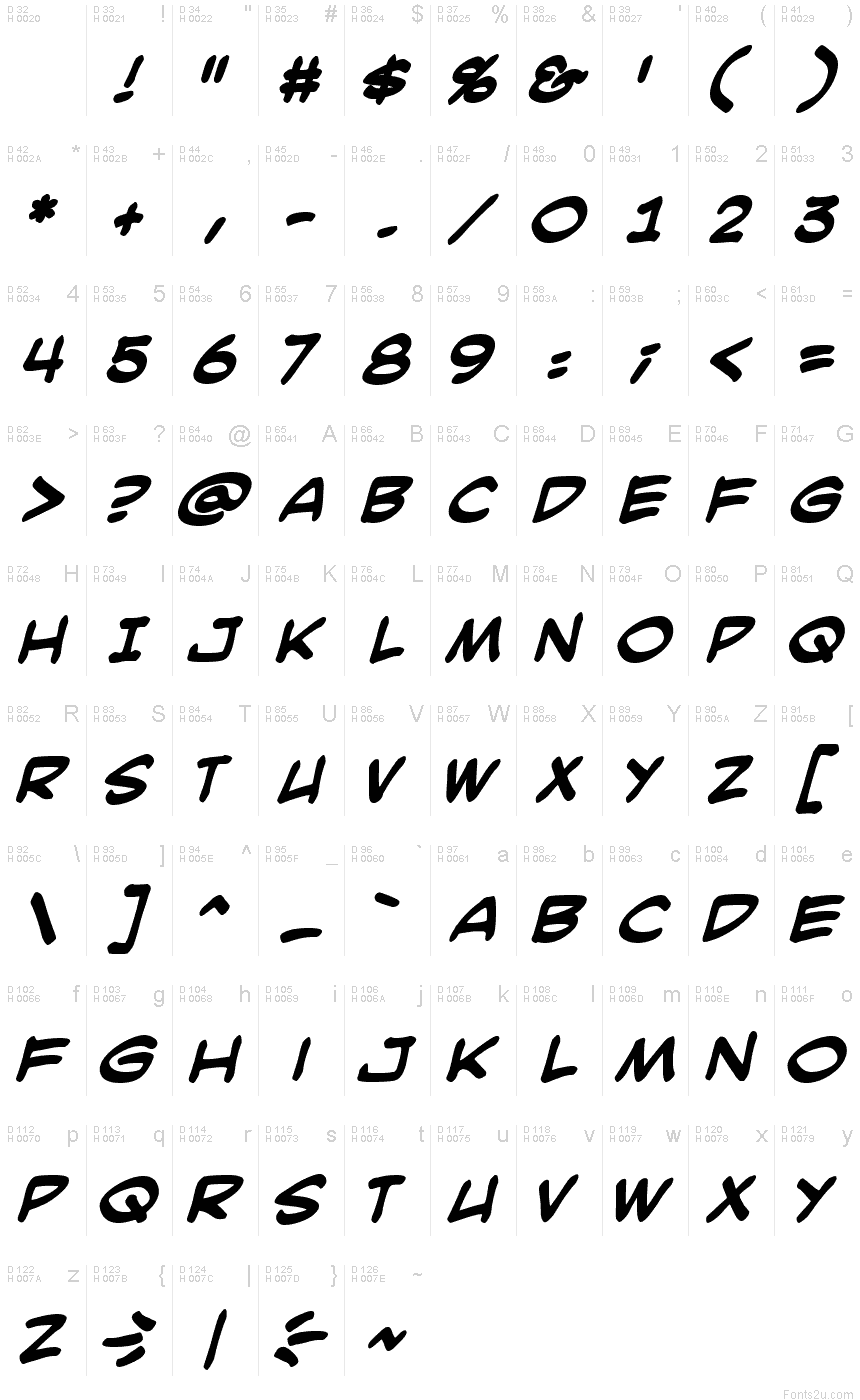
Smack Attack BB Bold di Nate Piekos è un font display gratuito in stile fumetto, con un carattere rapido e pennellato. Le lettere presentano tratti spessi, curvilinei e angoli netti, conferendo alle maiuscole un look "action" che comunica movimento, impatto e un pizzico di malizia.
Perfetto per poster, loghi di giochi, copertine di fumetti, titoli e grafiche per merchandising dove serve energia immediata senza rigidità. Usalo per titoli brevi, onomatopee o scritte accattivanti sulle confezioni: le curve ampie e le estremità appuntite rendono vivace anche la riga di testo più breve.